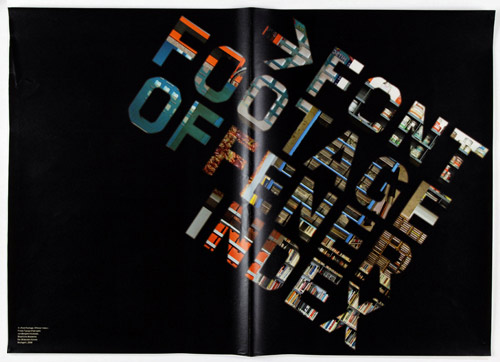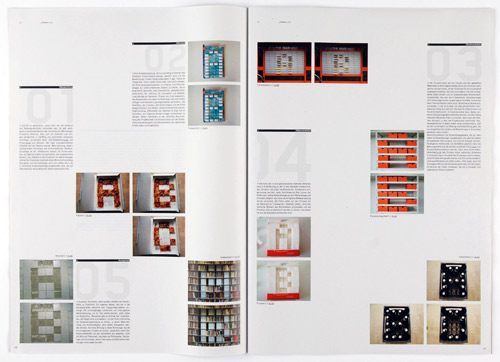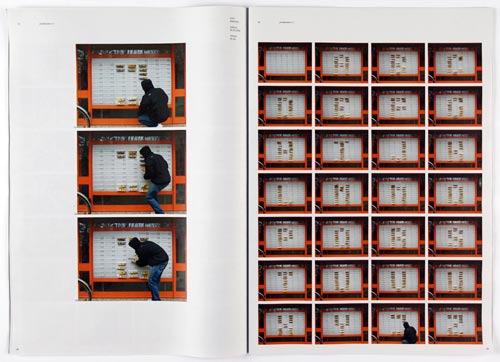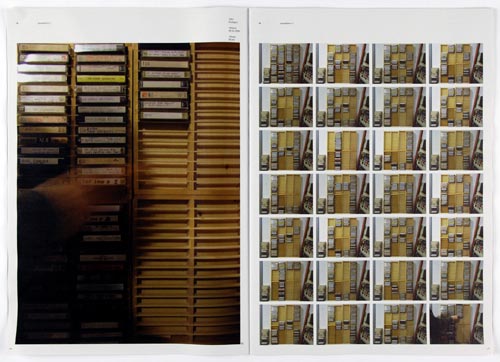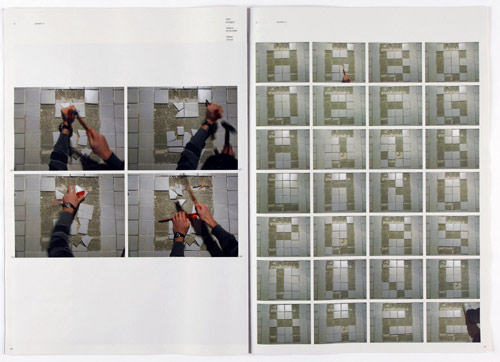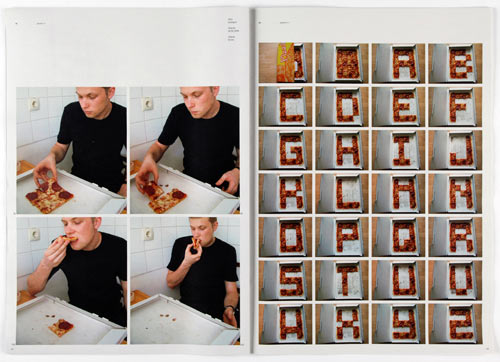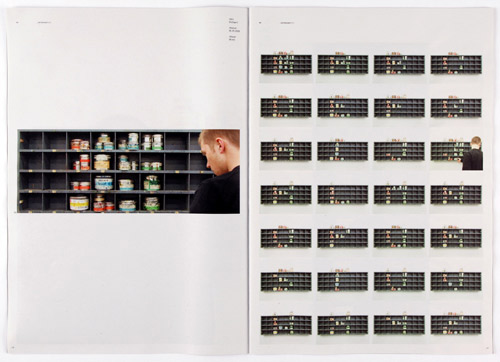
“Font Footage: Offener Index” ist ein DIN A3 formatiges Heft, dass sich experimentell mit, vom Alltag gegebenen, Rastern und zugehörigen Buchstaben auseinandersetzt. Das Heft umfasst 40 Seiten und wurde in einer kleinen Auflage 4 farbig, digital gedruckt. Das Projekt entstand im Rahmen eines “Freien Typografie Projektes”, bei Professor Gerwin Schmidt an der Akademie Der Bildenden Künste Stuttgart.
Schrift zu generieren, muss nicht mit viel Aufwand und Reibungsverlusten verbunden sein, dies zeigt sehr schön die Arbeit von Benjamin Kivikoski. Es gibt genügend vorsystematisiertes oder mit einfachen Werkzeugen formbares Material, dass sich mit Spielwitz und einigen Handgriffen in vielfältig und unmittelbar nutzbares Schriftgut verwandeln lässt: Getränkekisten, Pizzen, Kartons, Fliesen usw.
Die Dokumentation wurde mit einer herkömmlichen Fotokamera aufgenommen. Jeder Buchstabe ein Bild, immer der Reihe nach, kleine Abwandlungen je nach Materiallage und Ortswahl möglich, was die Schrift lebendig erscheinen lässt. Auf eine nachträgliche Bildbearbeitung wurde verzichtet. Je gröber das Raster, desto größer die Nähe der Rasterfonts zu Pixelfonts.